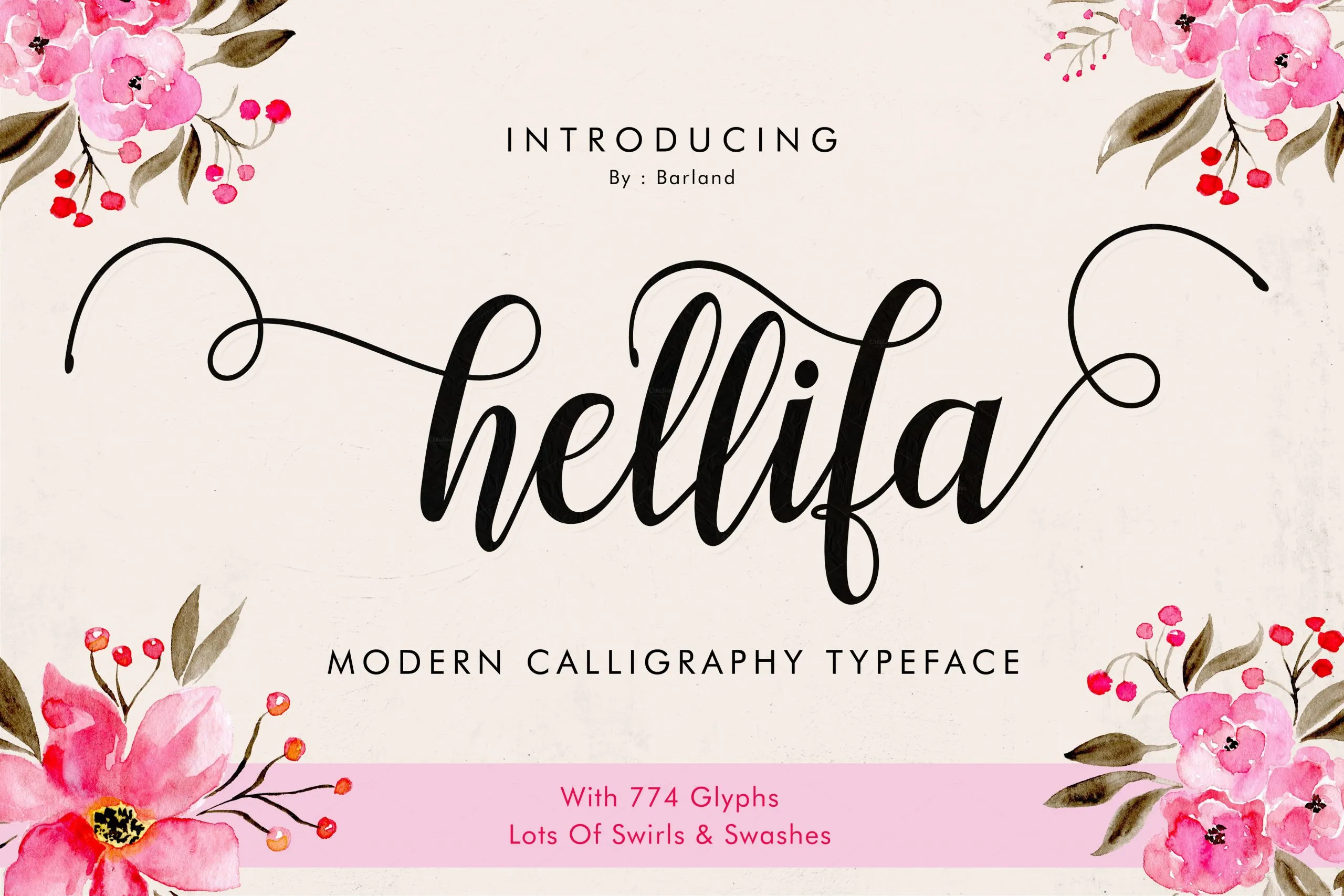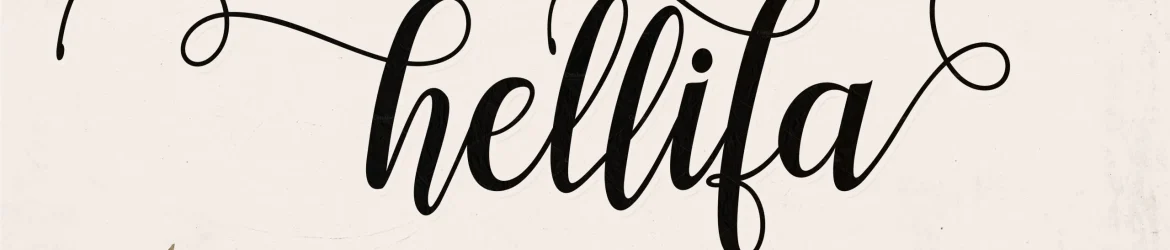
Hellifa Script Font – Download Grátis
Hellifa Script é uma nova e moderna fonte de script que traz elementos únicos ao seu trabalho de criação de materiais digitais. Esta fonte traz características decorativas e um estilo de escrita artesanal, criando texturas efeitos únicos que podem enriquecer sua identidade visual. Suas linhas delicadas e acentos elegantes tornam Hellifa Script perfeito para o design de cartões de convite ou cards de negócios, bem como para materiais branding e até mesmo postais. Suas características distintivas também são úteis para ilustrar citações, criar posters atrativos e adicionar um toque único a qualquer projeto que você estiver trabalhando. Com Hellifa Script na sua coleção, os seus projetos serão encantadores e impecavelmente detalhados. Com o designer Barland trazendo essa fonte cheia de personalidade para a comunidade dos criadores digitais, Hellifa Script é uma escolha perfeita para aqueles que buscam adicionar um toque único e moderno à sua identidade visual. Suas linhas delicadas e detalhes refinados permitem que você possa explorar a criação de materiais como cartões de convite, cards de negócios ou posters, garantindo sempre que seu trabalho seja atraente e memorável.